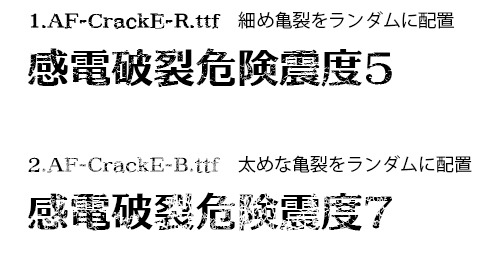
本商品は下記2書体のセットです。
1)AF-CrackE-R.ttf 細め亀裂をランダムに配置
2)AF-CrackE-B.ttf 太めな亀裂をランダムに配置
AF-クラックは太めの明朝体をベースにひび割れた形状で危険を強調する為のデザインフォントです。大見出し、危険の強調、動画テロップやサムネイルへの応用にご検討ください。